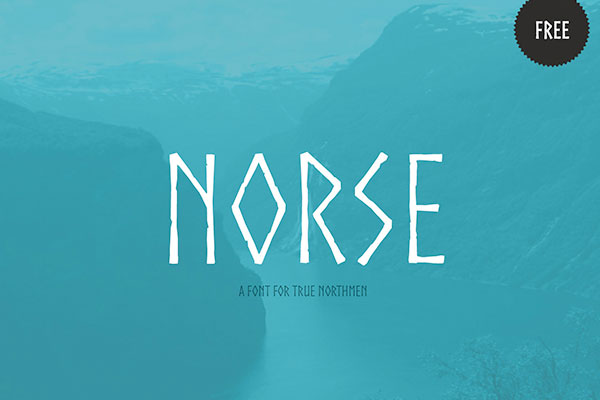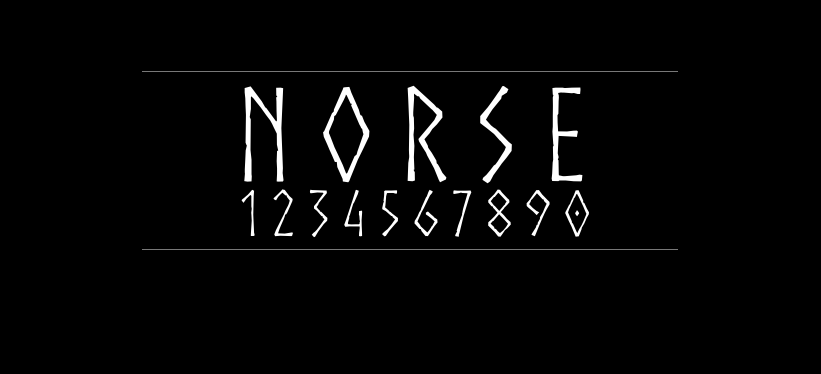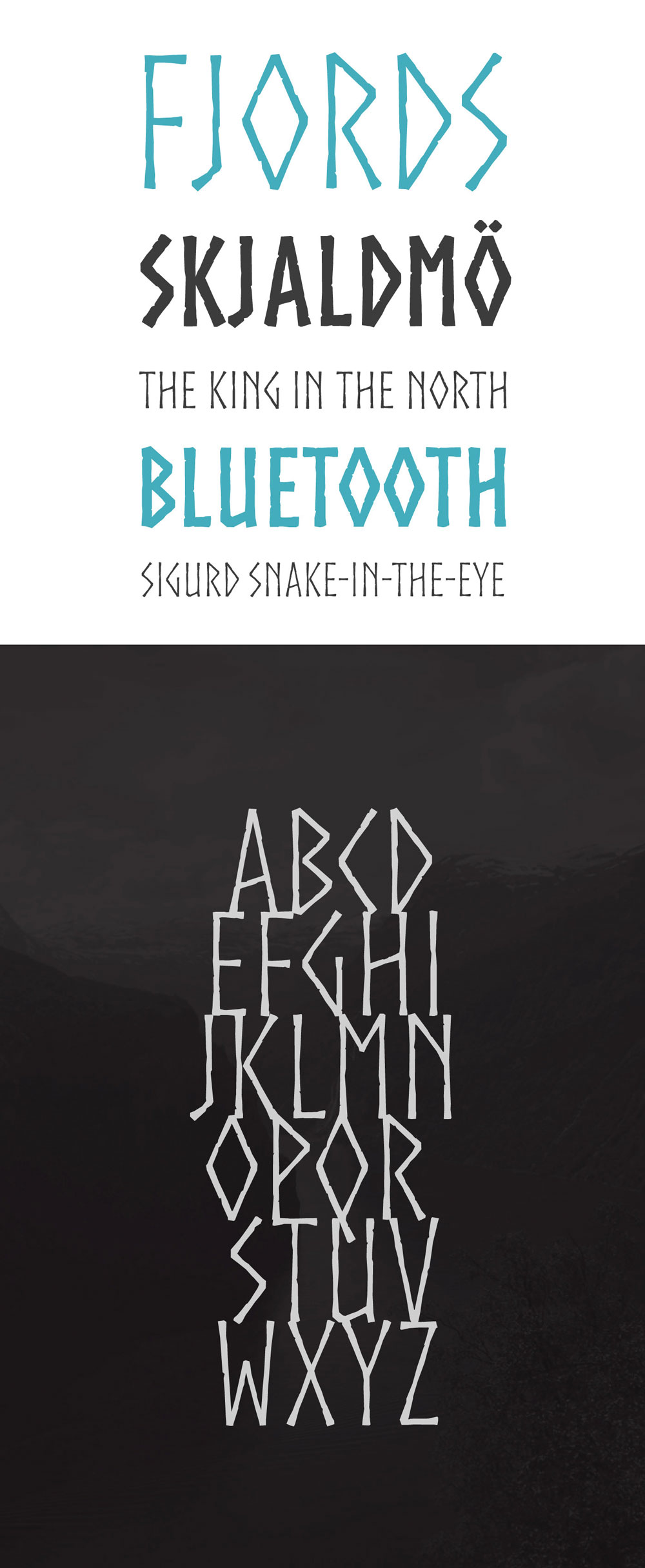
Norse
Norse的作者是来自法国的Joël Carrouché,该字体的创作受北欧铭文的启发,它是专为文化杂志和卡片设计的。字体包括2个字重,并带有unicode支持的完整符文字母。
如果您正在寻找一种独特的字体来销售与电影,故事,视频游戏,电视节目,杂志或邀请卡中的传说和神话有关的主题,那么JoëlCarrouché的这种显示字体非常适合您。您可以免费下载它,并将其用于个人和商业项目。